Красная рубрикация: как средневековая книга делила текст цветом
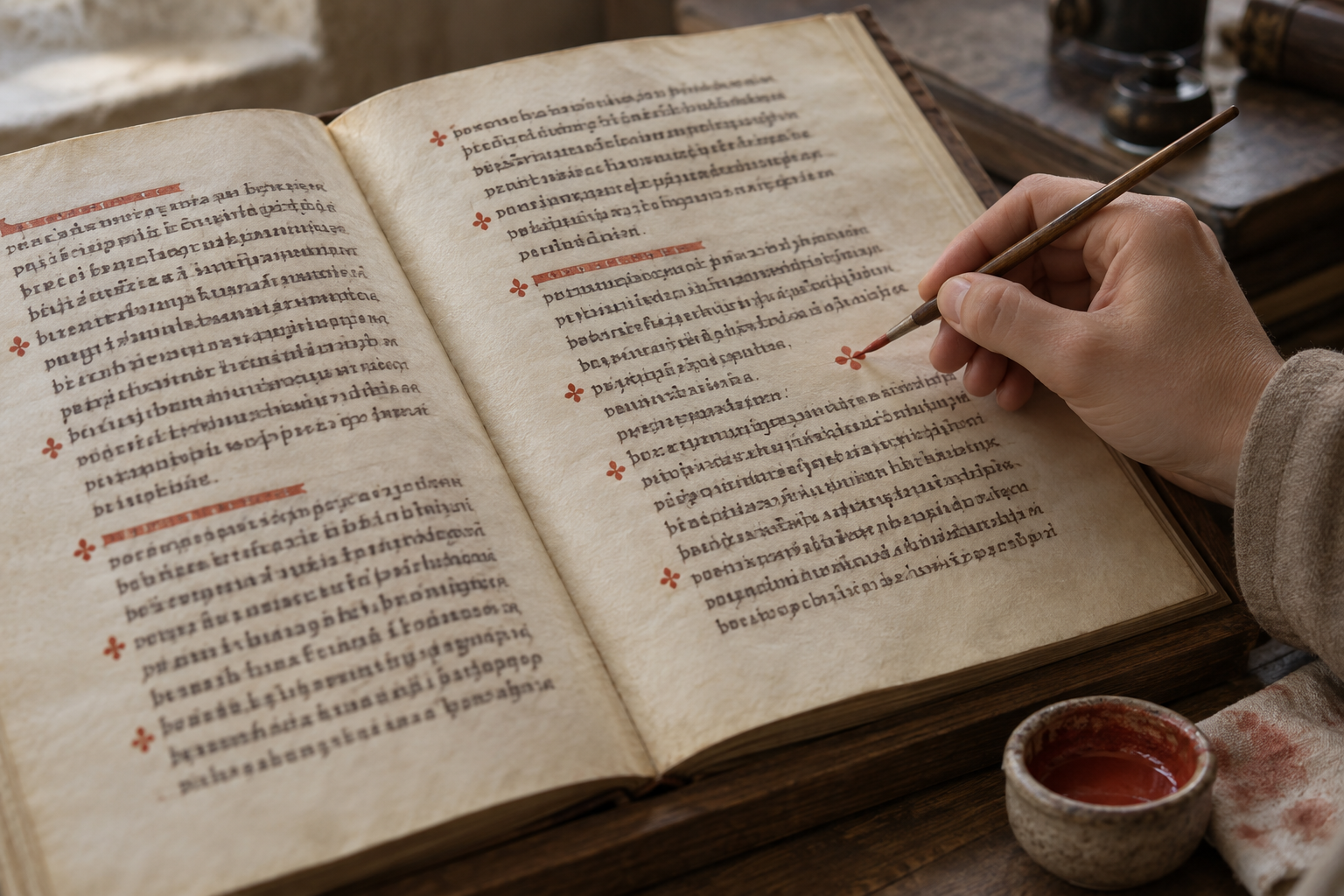
Рубрикация — система красных заголовков, помет и выделений, которая помогала читателю быстро находить начало раздела, важное имя или нужную инструкцию в рукописной книге. Это не просто украшение и не то же самое, что большая орнаментальная буквица. Разберём, как читать эти сигналы на страницах подлинных рукописей и как перенести их логику в современную типографическую иерархию.
Что называют рубрикацией
Слово связано с латинским rubrica — красной землёй, мелом или краской; в книжном контексте рубрикацией называют красные элементы, добавленные к основному тексту. Это могли быть заголовки, названия глав, короткие инструкции, выделенные инициалы, подчёркивания и знаки абзаца. Британская библиотека описывает рубрикатора как писца, который вносил такие пометы в уже размеченный и переписанный кодекс: красный цвет отделял части книги и помогал ориентироваться. На полях иногда оставляли указания, где именно добавить красный текст (British Library: The colour red).
Важно не сводить понятие к одному красному заголовку. Рубрикация — это визуальная система: разные масштабы, повторяющиеся места на странице, связь с чёрным основным текстом. Красный мог обозначать начало крупной части, более скромная черта — внутренний поворот, а повторяющиеся маркеры — последовательность однотипных элементов. Конкретные решения менялись от книги к книге: их нужно читать по самому кодексу, а не переносить на все эпохи как универсальное правило.
Рубрикация также не равна буквице. Буквица — увеличенная начальная буква, часто украшенная; рубрикация может включать её, но охватывает и множество менее крупных сигналов. Для редактора макета это полезное различие: если нужен декоративный акцент в начале статьи, достаточно буквицы; если нужно показать устройство длинного материала, важнее система заголовков, маркеров и цветовых акцентов.
Как цвет строил навигацию на странице
Рассматривайте страницу как маршрут. Чёрный или тёмно-коричневый основной текст несёт непрерывное чтение. Красный элемент прерывает поток и сообщает: здесь начинается другая функция. Читатель может продолжить строку, заметить новую часть, перескочить к нужному месту или вернуться к разделу. Рубрикация тем самым работает на трёх уровнях:
- Навигация: заголовок или короткая формула позволяет найти раздел без последовательного чтения всей страницы.
- Сегментация: красная буква, знак или линия показывает границу между соседними частями.
- Приоритет: размер и насыщенность отличают главное начало от регулярной внутренней отметки.
В рукописи Британской библиотеки Cotton MS Tiberius E IV каталог отмечает красные рубрики, выделенные красным римские числа и буквы, а также разноцветные монограммы в календарной части. Рукопись содержит материалы разных рук и датируется диапазоном от первой половины XII до первой четверти XIV века; поэтому это полезный пример не «единого средневекового шаблона», а сосуществования нескольких визуальных приёмов в одном составном кодексе. Факсимиле и описание доступны в каталоге рукописей Британской библиотеки, раздел Digitised Content.
Другой пример — книга Григория Великого Homilies on Ezekiel, переписанная для аббатства Хюйсбург в 1466 году. В каталоге Purdue University для неё описаны красные рубрики и знаки абзаца, инициалы, чередующиеся красно-синие знаки и крупные красно-синие орнаментальные инициалы на определённых листах. Этот объект показывает, что один кодекс мог сочетать функциональную разметку с украшением, но масштабы и задачи этих элементов различались (описание и доступ к оцифровке). При сравнении проверяйте конкретный лист: каталог перечисляет приёмы, а не утверждает, что каждый из них встречается на каждой странице.
Как читать красные сигналы, не приписывая им лишнего
Начинайте с контекста. Увидев красный текст, выясните, отделён ли он пробелом от основного набора, стоит ли в начале главы, повторяется ли перед одинаковыми частями и связан ли с соседним знаком. Один цвет сам по себе не сообщает функцию. Короткое красное слово может быть заголовком, указанием для чтения, началом текста или поздней пометой; без позиции и сопоставления соседних страниц уверенный вывод невозможен.
Затем сравните несколько уровней. Где крупное начало? Каким знаком отмечен обычный абзац? Как читатель узнаёт, что начинается новая часть? Различается ли начертание, размер или только цвет? Повторяемость даёт ключ: элемент, появляющийся в одном и том же месте нескольких глав, скорее является частью системной навигации, чем случайным украшением.
Для источника, где цвет выцвел или плохо воспроизводится, используйте качественную цифровую копию и сравнивайте её с описанием учреждения. Скан может искажать оттенок, а монитор — усиливать или ослаблять насыщенность. Не восстанавливайте первоначальный пигмент по изображению на экране, если задача — историческое исследование; для дизайна же достаточно аккуратно зафиксировать, где находился акцент, какого он был масштаба и к чему относился.
Как перенести принцип в современный макет
Современный макет не должен буквально имитировать пергамент, красную краску или средневековую страницу. Полезно перенести функцию: один устойчивый визуальный код отвечает за один тип информации. Например, заголовки разделов можно выделить цветом, а маркеры действий оставить нейтральными; повторять цветовую функцию по всему документу; сохранять контраст и доступность текста.